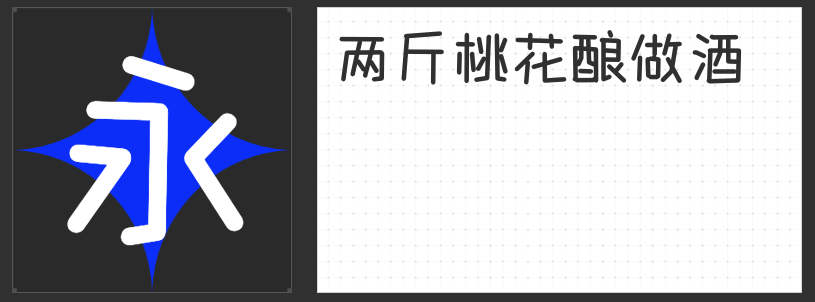
圆润灵动,设计新宠:四款特色圆体字体推荐
在视觉设计领域,圆体字体凭借其柔和的线条与独特的亲和力,成为品牌塑造、视觉传达的重要工具。以下四款兼具艺术性与实用性的圆体字库,以创新设计突破传统框架,为设计师提供多元选择。
一、励字圆梦简 中黑
作为励字造梦字库的代表作,励字圆梦简 中黑以“外圆内方”为设计核心,将黑体的稳重结构与圆体的柔和线条巧妙融合。其笔画采用直线设计,竖折替代弧线,既保持简洁明快的视觉节奏,又通过起笔、收笔及转折处的自然圆弧处理,赋予字体灵动气质。中宫松散的设计理念,使字符内部留白均匀,既适合标题的视觉冲击,也能胜任正文的长时间阅读需求。
二、字圈也字多肉体
字圈也字多肉体以“破方为圆”的创新理念,将传统汉字的直角转折转化为流动感圆弧,形成独特的封闭圆环结构。这种设计不仅弱化了字体的机械感,更通过饱满的笔画与圆润的轮廓,传递出温暖亲切的视觉情绪。其字形犹如充满弹性的软糖,在保持辨识度的同时,为品牌注入年轻化、趣味化的个性标签,尤其适合文创、儿童教育等领域的视觉呈现。
三、励字粗圆简繁
励字粗圆简繁以“方正饱满”为结构基础,通过加粗笔画与柔和转角,构建出端庄大气的视觉形态。其字面较大、中宫紧凑的设计,使字符在保持清晰可读性的同时,展现出强烈的存在感。笔形处理上,直线与圆弧的过渡自然流畅,既保留了黑体的力量感,又通过圆角弱化锐利感,形成刚柔并济的独特气质,适用于需要强调权威性与亲和力的双重场景。
四、高手庆科可爱体
由知名设计师郑庆科打造的高手庆科可爱体,以“去钩化”与“等粗化”设计突破传统手写体框架。其笔画端点与折笔处均采用半径4pt的圆角处理,竖弯钩、竖钩等部件通过简化设计提升整体简洁度,内部留白均匀的布局则确保了阅读舒适性。这款字体既保留了手写书法的自然韵律,又通过标准化处理适配数字屏幕显示,成为品牌年轻化转型的优质选择。
四款字体虽风格各异,却共同诠释了圆体设计的核心价值——在理性结构中融入感性温度,于规范框架内探索创新可能。无论是追求现代感的科技品牌,还是强调情感共鸣的文创项目,这些字体都能以独特的视觉语言,为设计注入鲜活生命力。